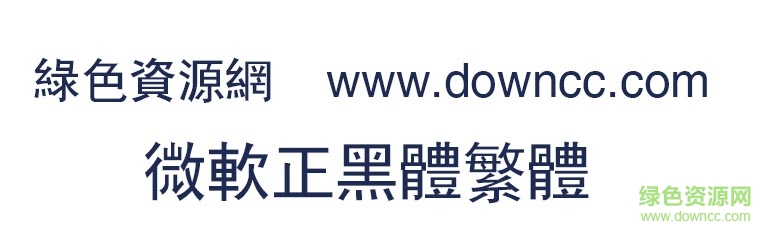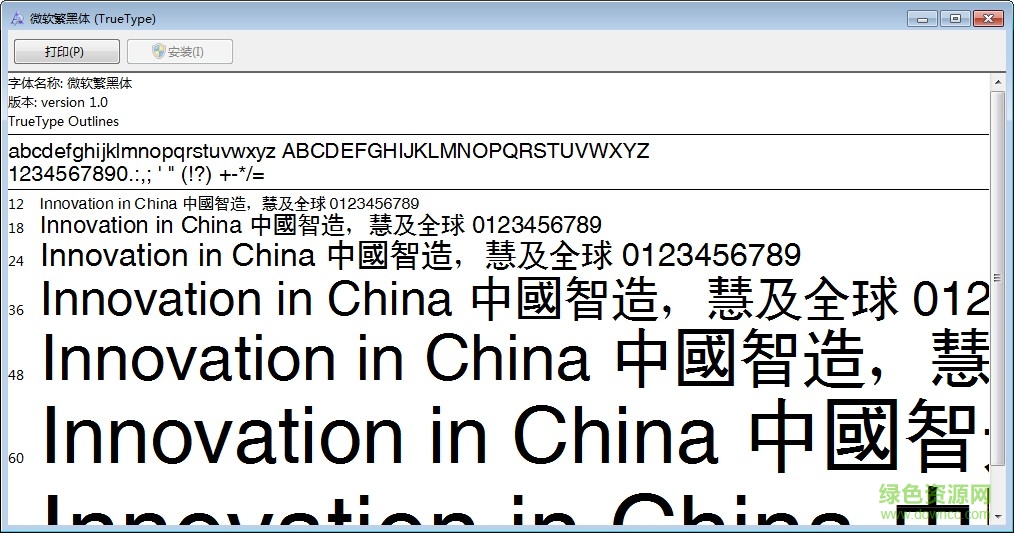
微軟正黑體繁體是一款非常有特色的電腦黑體繁體字體,整體筆畫看起來清晰,易于閱讀,適用范圍廣泛。從設(shè)計到制作再到審稿及全部字形的校對每一個環(huán)節(jié)都精心完成,確保字庫質(zhì)量的精良,喜歡可以來綠色資源網(wǎng)下載體驗!
一種支持大字符集的開源字體,可用于正文、小標(biāo)題、大標(biāo)題、海報、大型牌匾及屏顯用字。整個系列風(fēng)格完全一致,不管是常用字或是非常用字,字字精美、結(jié)構(gòu)端正、重心平穩(wěn)、美觀實用。